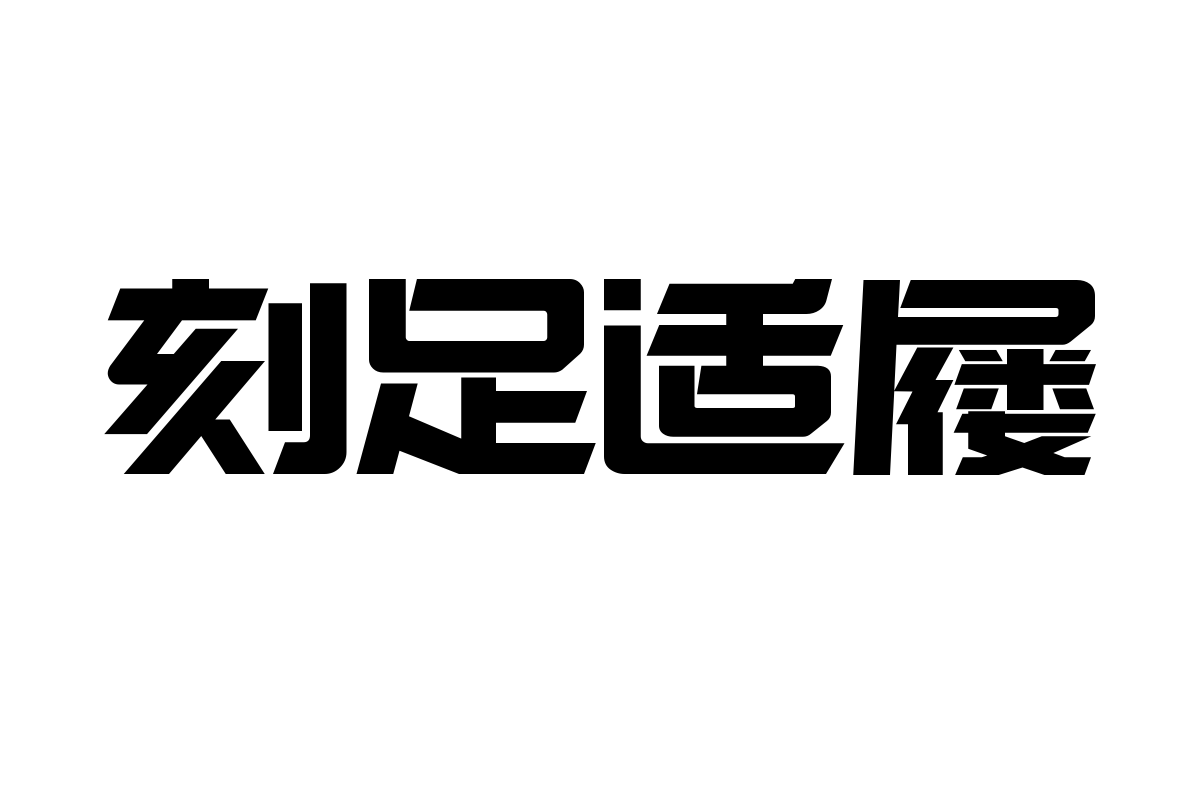
造字工房凌黑体是一款由造字工房公司推出的免费开源字体,具有独特的设计风格和丰富的字形变化。这款字体适用于各种设计场景,如海报、广告、书籍封面等。
造字工房凌黑体的特点包括:
1. 字形美观:该字体的字形结构紧凑,线条流畅,整体视觉效果优雅大方。
2. 字形丰富:造字工房凌黑体的字形变化多样,可以根据不同的设计需求进行选择和组合,满足个性化的设计要求。
3. 支持多种字体大小:该字体支持多种字体大小,可以根据设计需求进行调整,以适应不同场景的应用。
4. 可自由编辑:造字工房凌黑体提供了丰富的字形库,用户可以根据自己的需要对字体进行编辑和调整,以满足个性化的设计需求。
总之,造字工房凌黑体是一款功能强大、风格独特的免费开源字体,适用于各种设计场景,值得设计师们尝试使用。